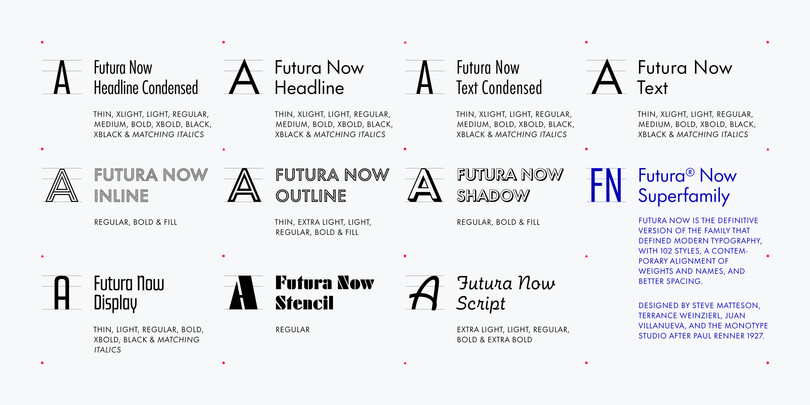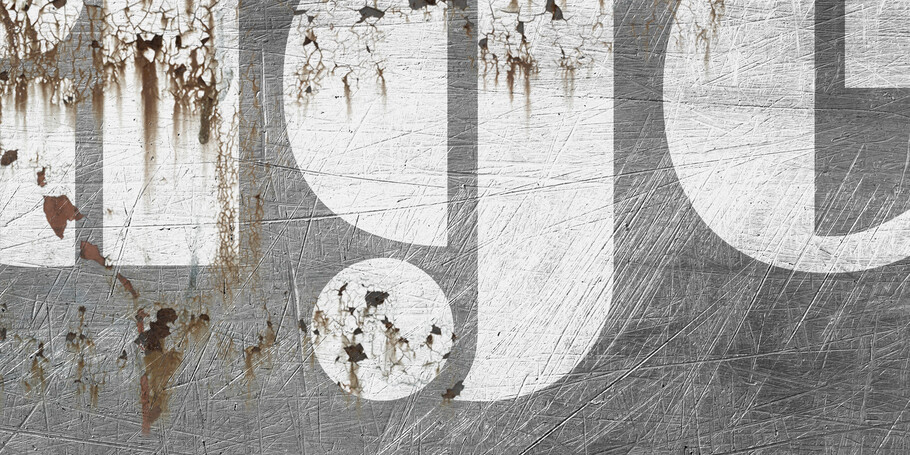
La Futura originale peut-elle bien se démarquer ?
“ Futura peut même être lue sur la lune. C’est elle qui annonce WE CAME IN PEACE FOR ALL MANKIND sur la plaque de la NASA que les astronautes ont laissée derrière eux en 1969. ”
Futura Now, la dernière famille créée par Monotype, est une renaissance et une extension de la célèbre police de caractères que nous connaissons tous si bien. Mais la connaissons-nous aussi bien que nous le pensons ?
Si Futura vous est familière, vous avez sans doute l’impression d’avoir baigné dedans toute votre vie : sur les panneaux, les affiches, les publicités, dans l’art. La prestigieuse géométrique sans serif a joué un rôle éminent dans la culture populaire des 93 dernières années.
Futura, c’est Nike qui nous invite à “Just Do It”. C’est le look de Volkswagen, Ikea, Louis Vuitton et d’innombrables autres marques au fil des décennies.
Futura peut même être lue sur la lune. C’est elle qui annonce WE CAME IN PEACE FOR ALL MANKIND sur la plaque de la NASA que les astronautes ont laissée derrière eux en 1969.
Ici, sur Terre, quand nous croisons désormais Futura, ce que l’on voit n’est probablement qu’une approximation de la police. Une descendante. Une aspirante. Certaines de ces polices presque-Futura portent son nom, d’autres non. Mais toutes tentent de capter l’apparence unique et l’essence générale de ce que la Fonderie Bauer a présenté en 1927 comme étant « la typographie d’aujourd’hui et de demain ».
Futura n’était pas la première géométrique sans serif lorsqu’elle est sortie (Erbar-Grotesk est parue en 1926, Kabel en 1927) et d’innombrables autres ont bientôt suivi (et suivent encore). Pourtant, Futura a réussi à s’inscrire dans le paysage populaire avec une fermeté que n’importe quelle marque pourrait lui envier.
Le passé de Futura.
La “vraie” Futura a été dessinée par Paul Renner pour la Fonderie Bauer en Allemagne entre 1924 et 1926. Il estimait, selon ses mots, qu’une « police de caractères faite pour l’état d’esprit contemporain devrait être… exacte, précise et impersonnelle. Elle devrait être fonctionnelle et simplement ce qu’elle est, sans chichi. Si c’est une typographie imprimée, elle ne devrait pas chercher à imiter une écriture, quelle qu’elle soit. »
Futura wasn’t the first geometric sans serif when it was released, but its subtle, masterful design (and clever marketing) quickly established it as the geometric sans serif.  Image credit: Fontshop.com.
Avec Futura, il nous a offert une typographie “monoligne” épurée et moderniste basée sur des formes simples — le cercle, le carré, le triangle. En dépit des apparences, néanmoins, Futura est loin d’être simpliste. Pour s’assurer de l’harmonie entre chaque caractère et de leur facilité à être lus, Renner a élaboré des ajustements subtils, magistraux et cruciaux ainsi que des compensations optiques. Avec dextérité, il a intégré l’intemporalité des proportions classiques des lettres capitales à un design très minimaliste, lisse, moderne et progressiste. Il a créé quelque chose de si avant-gardiste que cela semble toujours contemporain près d’un siècle plus tard.
Futura et les presque-Futura.
Pour vendre Futura aux États-Unis, Bauer a vite déménagé pour s’établir à New York en 1927. La police de caractères a très bien été reçue et cet enthousiasme a donné le coup d’envoi de tout un tas d’imitations.
À l’origine, la seule fonderie autorisée à produire Futura en dehors de Bauer était Intertype à New York. En 1930 en France, Deberny & Peignot a également obtenu une licence. La fonderie a alors modifié la police pour son marché français — avec des ascendants et des descendants extra longs — et l’a appelée Europe.
Entre temps, pour éviter la voie de l’octroi de licence, de nombreuses autres fonderies ont créé leurs propres ersatz de Futura sous d’autres noms.
1927–1928 : Peu après la sortie de Futura, la Baltimore Type Foundry a créé une police presque identique appelée Airport Gothic.
1929–1930 : Linotype possédait le design de W. A. Dwiggins appelé Metro et l’a modifié pour le rendre plus ressemblant à Futura.
1930 : Vogue a passé commande à Intertype pour la création d’une police identique qui puisse fonctionner dans ses machines de composition. On lui donna le nom de Vogue.
1937 : Monotype a présenté Twentieth Century pour ses composeuses, encore une autre concurrente presque-Futura.
1939 : Linotype déploie ses propres imitations de Futura : la famille de polices Spartan.
En aucun cas ceci n’est une liste complète d’imitations. S’il existait une telle liste, elle ne cesserait de s’allonger. Futura était si désirable, en réalité, et si largement imitée-exploitée qu’un concept plus libre de son nom de marque a fini par émerger — un peu comme les essuie-tout que la plupart d’entre nous appellent Sopalin.
Voici un exemple parfait : dans un élan de génie marketing (et/ou de tromperie), les entreprises de composition de Baltimore ont commencé à adopter une approche qui pourrait ressembler à celle d’une personne qui vendrait aujourd’hui une montre «Roluxe» au coin d’une rue. Elles ont proposé une catégorie de géométriques sans serif appelée «Futuria».
Comme l’original, Futura Now est une police créée pour aujourd’hui et pour demain — et bien au-delà.